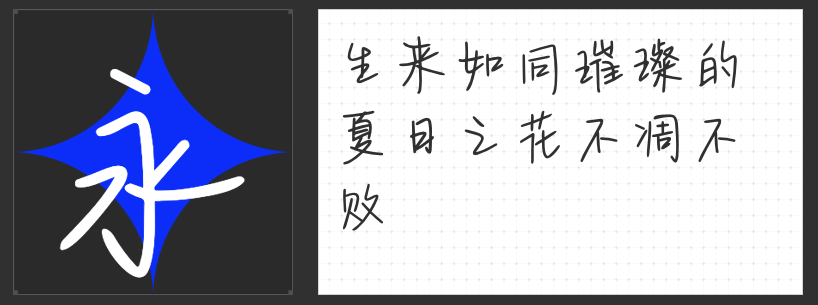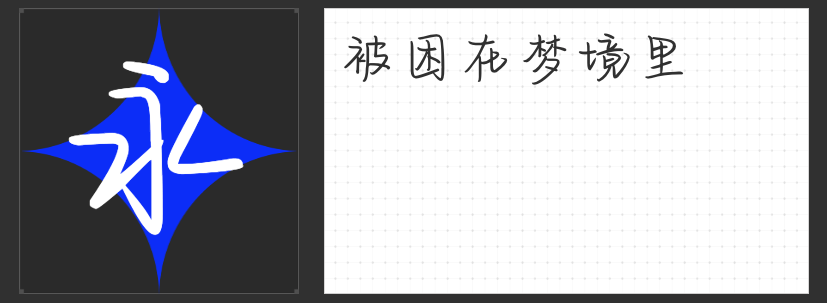
清新设计字体指南:四款灵动字型唤醒视觉呼吸感
在追求“少即是多”的清新设计语境中,字体的选择往往需要兼顾克制与个性——既要避免繁复的装饰喧宾夺主,又要通过独特的笔触传递情绪。以下四款字体以清秀笔触、自然韵律为核心,为短视频、海报、新媒体等场景注入轻盈的视觉呼吸感。
一、字青春悸动简
以“端正”为底色,这款字体通过纤细的笔画与适度的留白构建出通透的视觉秩序。横竖撇捺的起收笔干净利落,没有多余的装饰,却在细微的弧度中暗藏灵动——例如“心”字底的三点水以轻盈的曲线呼应,避免刻板。其字形结构如初春新芽,既保留了宋体的规整感,又以现代简化的笔触弱化传统字体的厚重,适合需要传递“清新而不失专业”的复合型场景。
二、励字造仲夏简
将斑驳的碑刻质感融入手写笔触,这款字体以“矛盾感”突破清新设计的同质化。坚挺的横竖笔画如竹节般挺拔,而钩笔处随性飞溅的墨点则像夏日骤雨,在理性框架中注入野性生命力。边缘的斑驳并非瑕疵,而是通过模拟纸张渗透的肌理,让字体仿佛从旧信笺中自然生长而出。这种“粗粝与精致并存”的特质,使其既能驾驭文艺海报的诗意,也能撑起商业包装的质感。
三、字圈也字半醒手迹
以“失衡感”制造视觉焦点,这款字体通过统一的倾斜角度与精准的重心控制,构建出动态的平衡美学。所有笔画均向右上方扬起,如被风吹斜的雨丝,却在紧密的中宫结构中保持稳定。这种“危险而优雅”的姿态,与电影海报中欲说还休的叙事、文艺话剧宣发中隐忍的情绪高度契合——字体的倾斜不是失控,而是将文字转化为视觉化的叹息。
四、高手兵克清秀体
去除了所有装饰性元素,这款字体以最纯粹的笔触还原手写的真实感。笔画粗细的微妙波动、转折处的自然顿挫,如同用铅笔在速写本上匆忙记录的灵感。其字形扁宽,重心偏低,营造出慵懒的松弛感,特别适合VLOG封面或Plog标题——那些需要传递“生活碎片中的小确幸”的场景,正需要这种不刻意的美。
这四款字体的共性在于“克制表达”:它们不依赖繁复的装饰或夸张的变形,而是通过笔触的呼吸感、结构的动态平衡、肌理的隐喻性,在有限的空间中构建丰富的视觉层次。无论是商业项目还是艺术创作,这种“清而不冷,秀而不弱”的特质,都能让设计在信息过载的时代保持独特的辨识度。